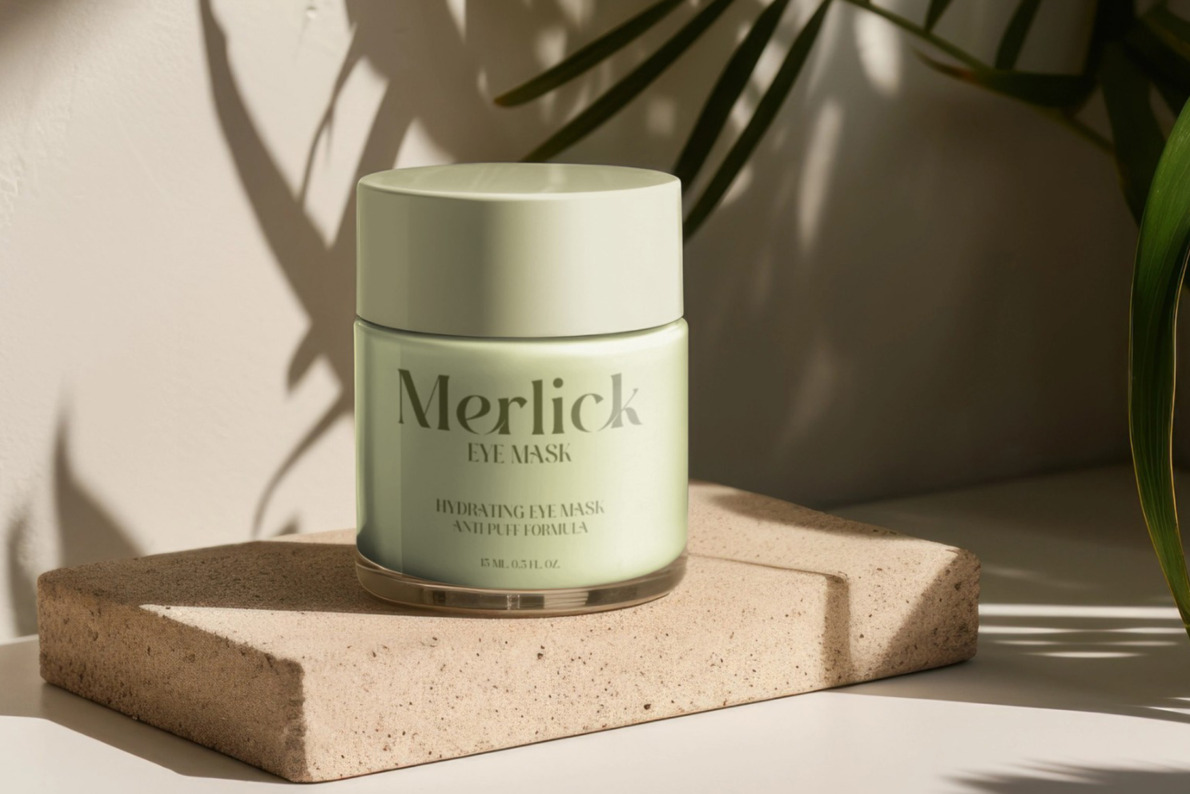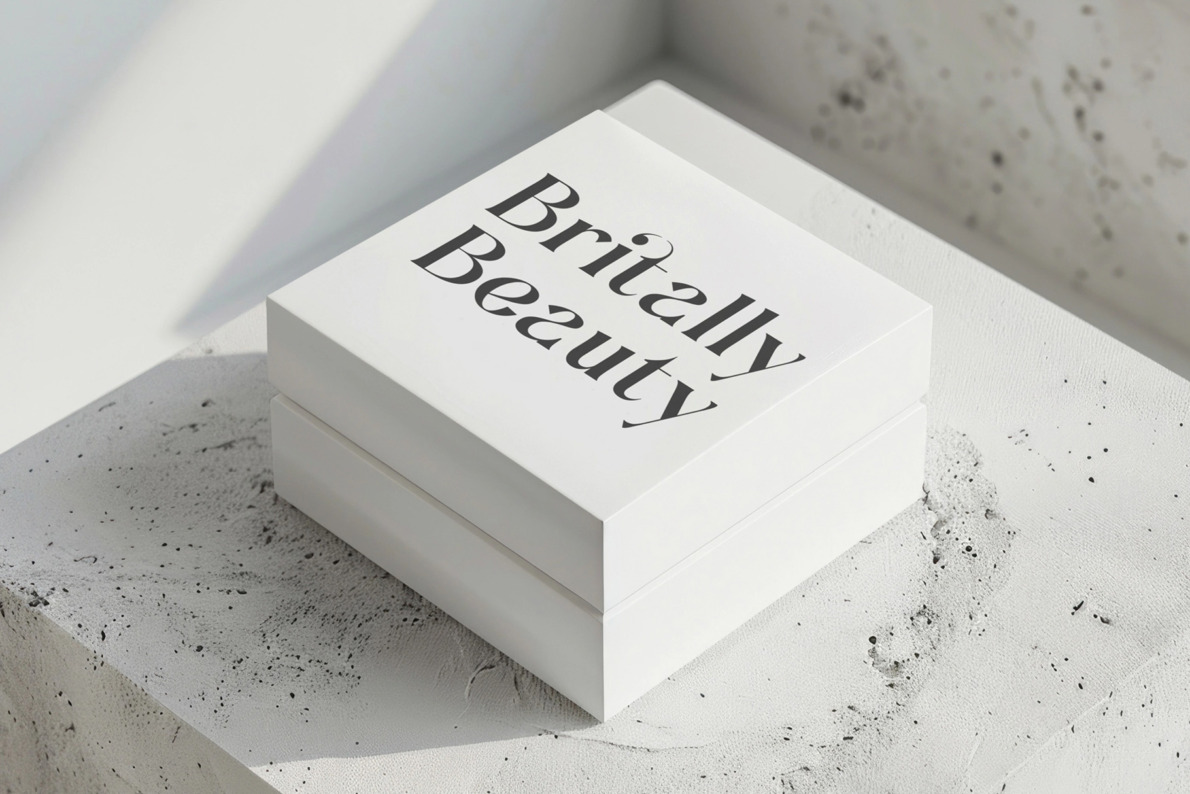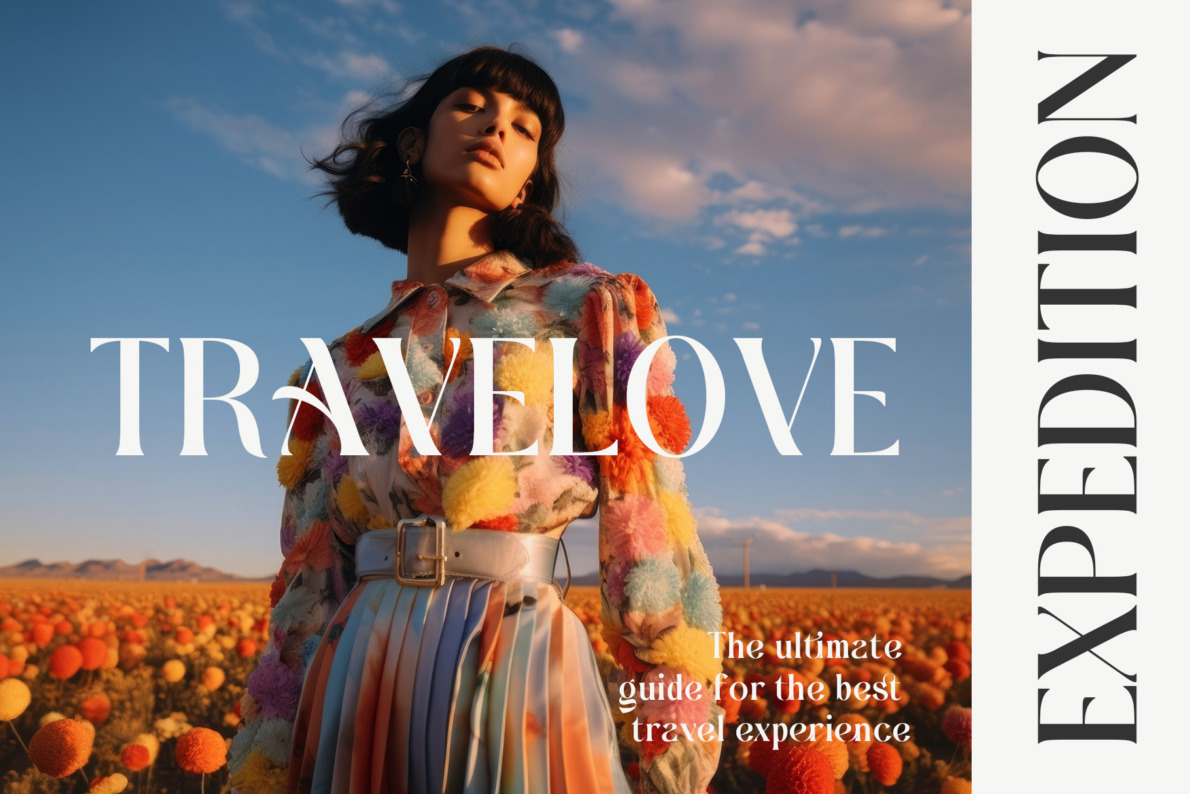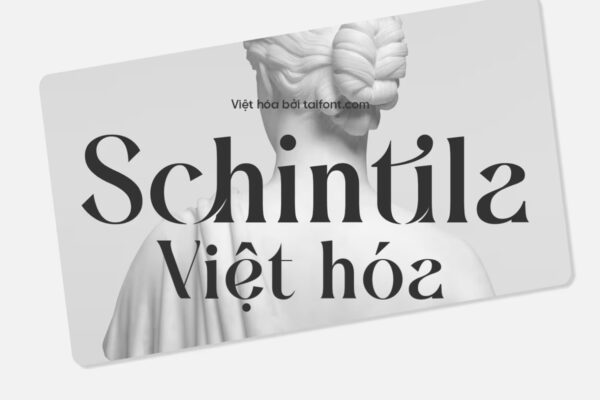
Giới thiệu về Font TF Schintila Việt hóa
TF Schintila Việt hóa là một font chữ có chân (serif) nổi bật với vẻ đẹp tinh tế, thanh lịch và đầy sang trọng, lý tưởng để tạo nên phong thái đẳng cấp và sự độc đáo cho các thiết kế. Font này được thiết kế với những đường nét được chăm chút tỉ mỉ, toát lên sự quý phái và duyên dáng, gợi cảm giác về sự hoàn hảo trong từng chi tiết.
Với sự tinh xảo trong từng ký tự và tính thẩm mỹ vượt trội, Schintila là lựa chọn hoàn hảo cho các ấn phẩm cần sự sang trọng và khác biệt, đặc biệt là trong ngành thời trang và mỹ phẩm:
- Thiết kế thời trang: Hoàn hảo cho các thương hiệu thời trang cao cấp, từ logo, nhãn mác sản phẩm, lookbook, đến các chiến dịch quảng bá bộ sưu tập. Font này giúp truyền tải vẻ đẹp thanh lịch, đẳng cấp và độc đáo của trang phục, nâng tầm giá trị thương hiệu.
- Thiết kế mỹ phẩm: Lý tưởng để sử dụng trên bao bì sản phẩm, nhãn mác, catalogue, hoặc các chiến dịch marketing của các thương hiệu mỹ phẩm cao cấp. Schintila giúp khẳng định chất lượng, sự sang trọng và vẻ đẹp tinh túy của sản phẩm, thu hút ánh nhìn của khách hàng và truyền tải thông điệp về sự quyến rũ, đẳng cấp.
- Thiết kế làm đẹp: Phù hợp cho các spa, thẩm mỹ viện, hoặc các dịch vụ làm đẹp cao cấp. Font có thể dùng trên bảng hiệu, menu dịch vụ, voucher hoặc các ấn phẩm quảng cáo, giúp truyền tải sự thư giãn, chuyên nghiệp và sang trọng.
Với TF Schintila Việt hóa, bạn có thể dễ dàng thổi hồn tinh tế, sang trọng và vẻ đẹp hoàn hảo vào các thiết kế, tạo ra những sản phẩm không chỉ đẹp mắt mà còn đầy cảm xúc và sức hút đặc biệt.
Font Việt hóa TF Schintila – Phong chữ tạp chí